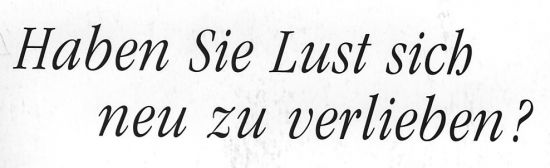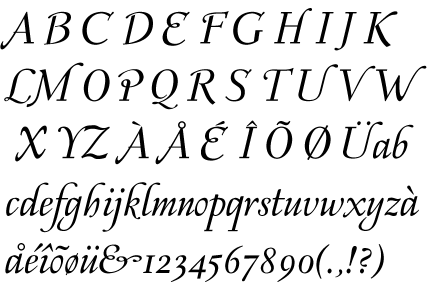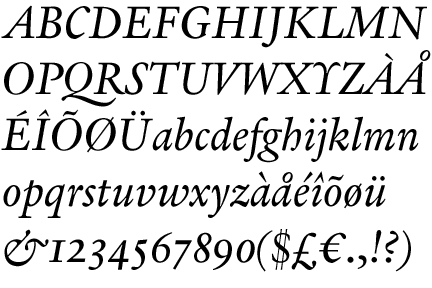
Suche Schriftart siehe Abb.
Hallo, kann mir jemand sagen welche Schriftart das ist und wo ich diese eventuell kostenlos erwerben kann?
Versuch mal Ronsard (abgesehen von den Versalien...)
oder MVB Verdigris Italic (is zwarn bissl fetter..)
Bin mir nicht ganz sicher, aber ich denke Verdigris passt besser..
Haha:) Da haste wohl recht Bertel.. ;) Hab ich wieder mal zu weit gesucht..
… Hab ich wieder mal zu weit gesucht..